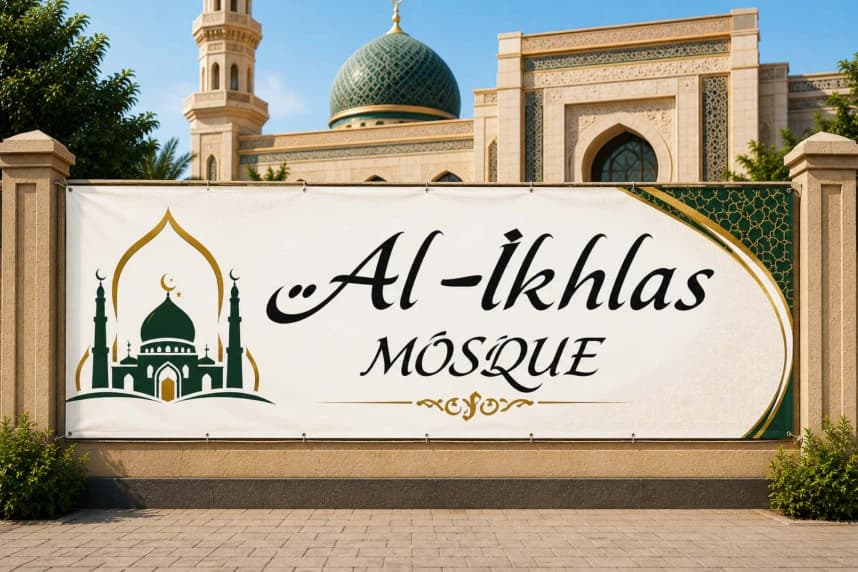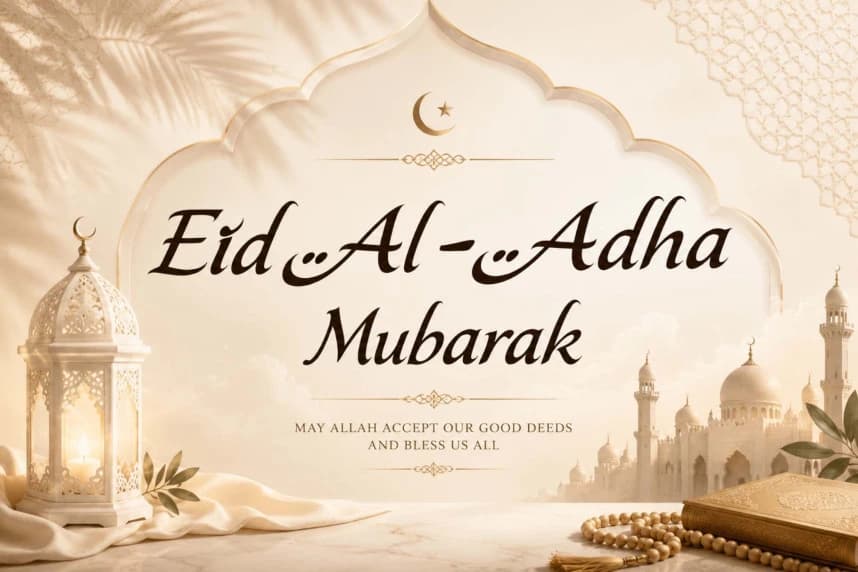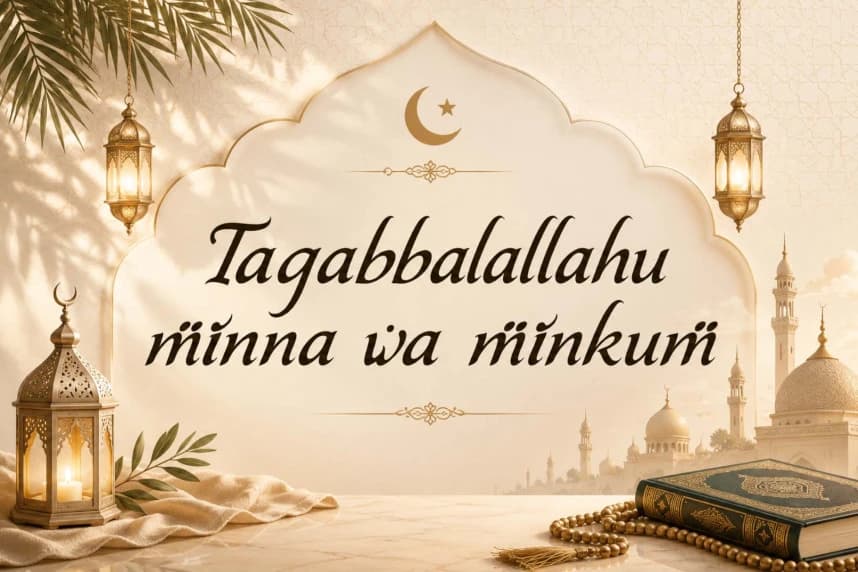
Qasrina Arapça Yazı Tipi
Qasrina Arabic Font zarif ve benzersiz bir Arapça gösterim yazı tipidir. İki stile sahiptir: regular ve italic. Büyük harfler ve küçük harfler, rakamlar, noktalama işaretleri ve çok dilli destek içerir.
Qasrina Arabic Font zarif ve benzersiz bir Arapça gösterim yazı tipidir. İki stile sahiptir: normal ve italik. Büyük ve küçük harfler, rakamlar, noktalama işaretleri ve çok dilli desteği içerir.